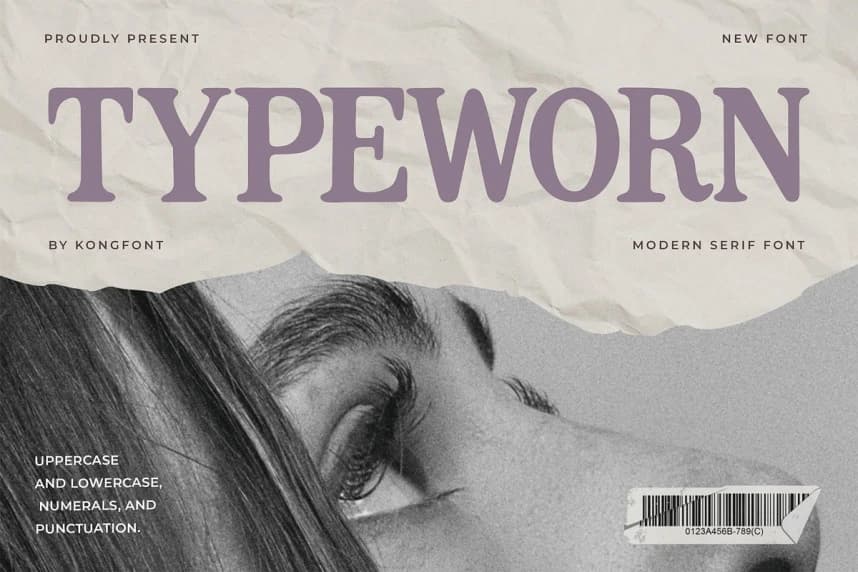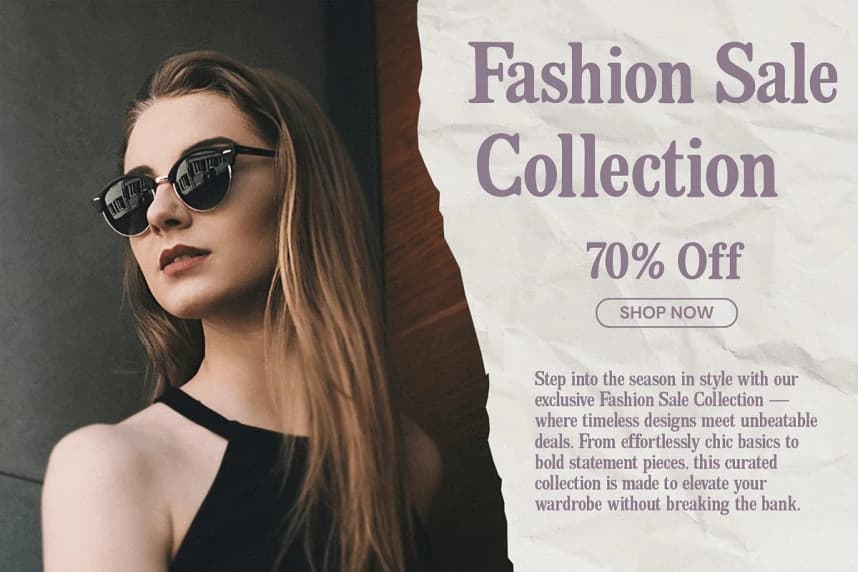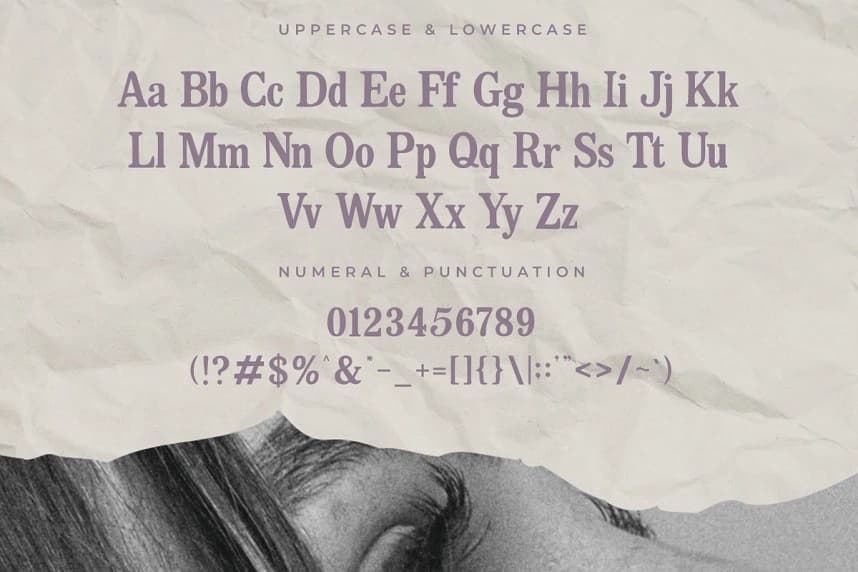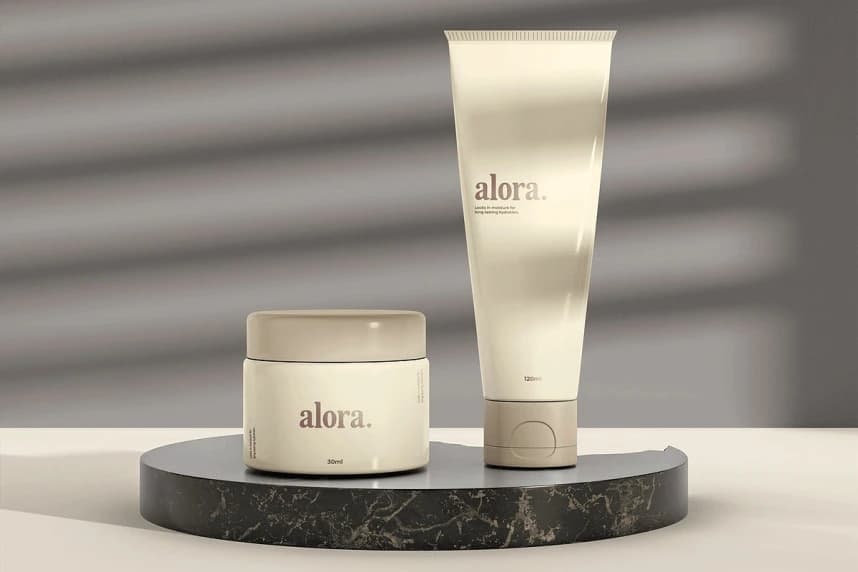
Typeworn Font
Typeworn Font, aşınmış bir görünüm ve vintage esintili bir hava taşıyan modern bir serif yazı tipidir. Nazikçe aşınmış harf biçimleri ve zarif serif detaylarıyla bu yazı tipi, eski baskı tipinin çekiciliğini çağrıştırırken modern tasarım kullanımı için temiz ve çok yönlü kalır.
Typeworn Font, yıpranmış, vintage esintili bir dokuyla modern bir serif yazı tipidir. Hafif aşınmış harf biçimlerine ve zarif serif ayrıntılarına sahip olan bu yazı tipi, eski basılı tiplerin cazibesini çağrıştırırken modern tasarım kullanımı için temiz ve çok yönlü kalır.